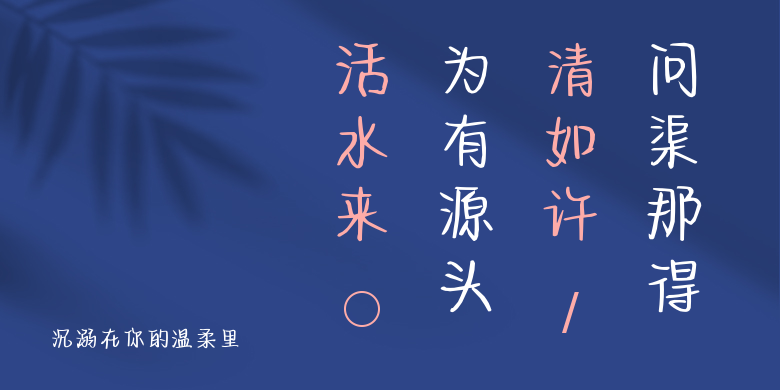
沉溺在你的温柔里
沉溺在你的温柔里,这款字体结构工整、笔画清晰,兼顾美观与易读性,适用于标题、正文、海报、包装、LOGO 等多种场景。字形优雅稳定,风格百搭耐看,适配日常排版与创意设计,让文字呈现更舒适、更具质感。沉溺在你的温柔里一笔一画,皆是细节,以均衡的比例、流畅的线条打造舒适视觉体验,字形端正大气,风格简约现代。无论是商业设计、品牌宣传还是日常排版,都能轻松驾驭,让文字更有格调与力量。沉溺在你的温柔里字体下载。